18 خطًا قوطيًا رائعًا للعروض والعناوين وتصميم الشعار (2022)
نشرت: 2022-10-17يجب أن تكون خطوط العرض واضحة وسهلة الفهم. ومع ذلك ، في بعض الحالات ، يمكنك استخدام نصوص مخطوطة حيث يستدعي التصميم (والقارئ الهدف) ذلك. قد تحتاج إلى إنشاء شعار لحلاق الرجال ، أو التركيز على علامة تجارية للكحول المعبأ ، أو استعادة بضع مئات من السنين. لهذا ، سترغب في اللجوء إلى الخطوط القوطية.
في هذا المنشور ، سنلقي نظرة على عدد من الخطوط القوطية ، ونمنحك مجموعة مختارة من الخطوط القوطية. قبل ذلك ، دعونا ننظر في ماهية الخطوط القوطية ، وكيفية العثور على الخط المناسب.
ما هو الخط القوطي (وما الذي تبحث عنه في الخط المثالي)
الخطوط القوطية لها تاريخ مثير للاهتمام ، وهناك تعريفان. الأول من خلال Blackletter - محرف أوروبي من القرنين الثاني عشر والسابع عشر. في الواقع ، يعد Blackletter أحد أهم محاور الطباعة الغربية ، جنبًا إلى جنب مع الأنواع المائلة والرومانية.
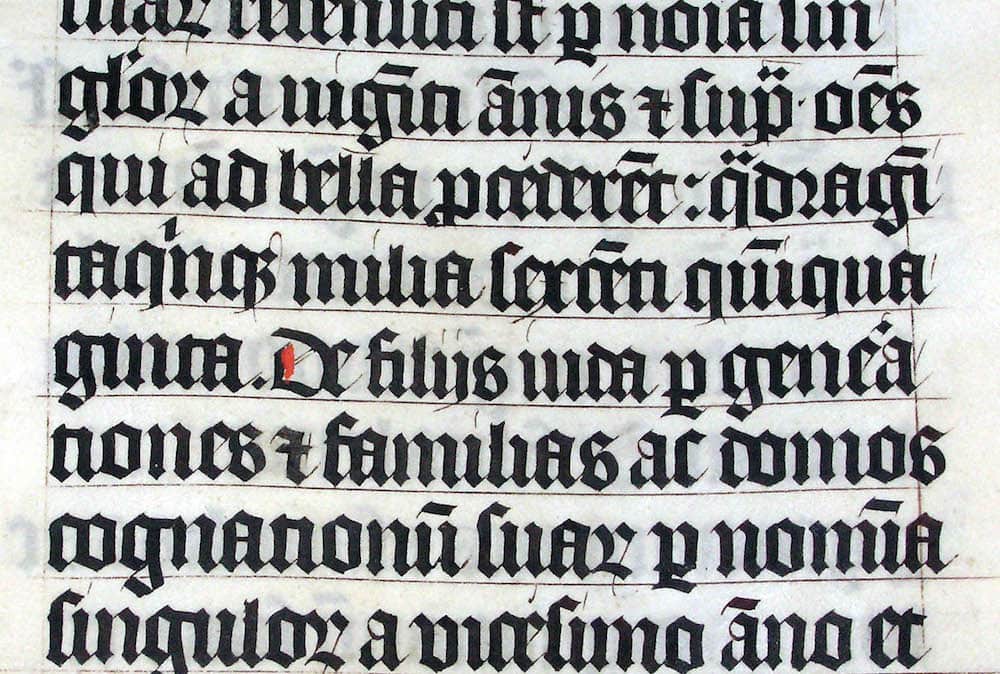
لديها عدد من الأسماء المختلفة - القوطية المصغرة ، و Blackletter ، والإنجليزية القديمة - ومجموعة متنوعة من الأشكال. يعتمد هذا على التفسيرات المختلفة في جميع أنحاء أوروبا ، والتي اعتبرت جميعها أن الخطوط القوطية "بربرية". على سبيل المثال ، Textura و Schwabacher و Fraktur و Cursiva و Hybrida.
المصطلح الآخر للخطوط القوطية يتعلق بالأسكندنافية “grotesk”. المحارف التي تستند إلى أشكال شمال أوروبا تشبه إلى حد كبير خطوط sans serif الكلاسيكية ، وفي كثير من الحالات يمكن أن تكون قابلة للتبديل.
كيفية اختيار الخطوط القوطية
يعتمد اختيارك للخط القوطي على النوع الذي تريد استخدامه. ومع ذلك ، من المحتمل أن ترغب في استخدام أحدهما كعنوان أو بأحجام أكبر. على سبيل المثال ، يمكن أن يتبع متغير grotesk نفس القواعد التي تتبعها sans serifs الأخرى في معظم الأحيان ، ولكنها قد تبدو مشتتة للغاية لنسختك الجسدية.
من المحتمل ألا يكون أسلوب الكتابة والنصوص في أوروبا الوسطى مناسبًا للنص الأساسي على الإطلاق ، على الرغم من أن هذه حالة استخدام نموذجية في أوجها. يمكن أن تكون هذه الأشكال غير قابلة للقراءة تمامًا في كثير من الحالات ، خاصة في الأحجام الأصغر - ومن ثم تكون الخطوط القوطية "بربرية".
نصيحتنا هي النظر في الطلب بإسهاب. ستكون الخطوط القوطية أفضل كعنوان أو كشعار لمستخدم مستهدف محدد.
18 خطًا قوطيًا رائعًا للعروض والعناوين وتصميم الشعار
خلال ما تبقى من هذا المنشور ، سنقوم بتشغيل بعض من أفضل الخطوط القوطية التي يمكن أن نجدها. طوال الوقت ، سنقدم لك أيضًا فكرة عن سعر كل منها ، إلى جانب مكان العثور عليها.
1. كامبريدج
تبدو كامبريدج وكأنها متغير "إنجليزي قديم" ، وستكون أفضل بأحجام كبيرة جدًا ، مثل الملصق أو التصميم المتناثر.
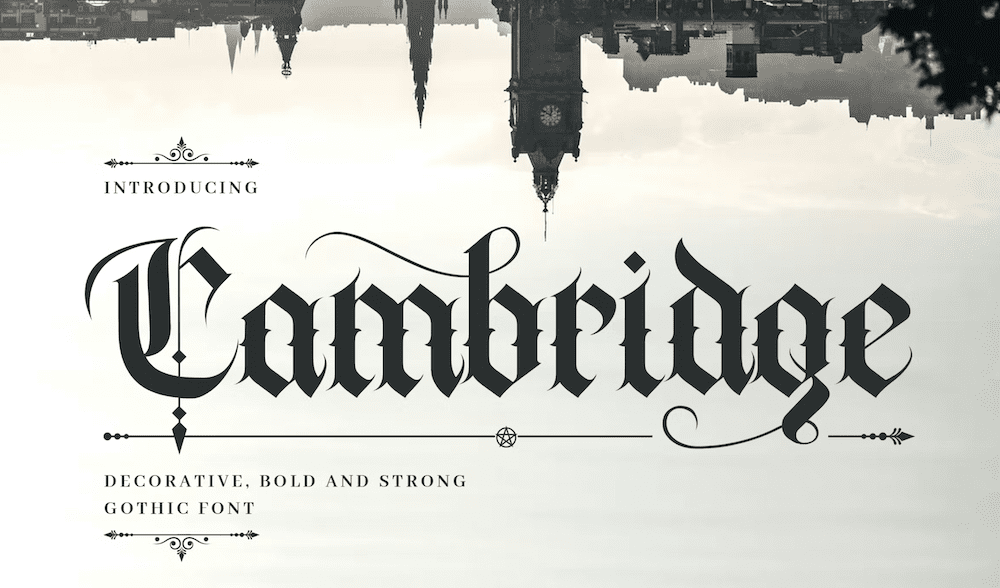
يأتي بثلاثة تنسيقات مختلفة - OTF و WOFF و TTF - ويتضمن مجموعة قياسية من الأحرف اللاتينية والأرقام وعلامات الترقيم والأحرف البديلة. كامبريدج مزخرفة ، ويمكن قراءتها بأحجام أصغر أيضًا - مما يثير الدهشة لمثل هذا الخط الخطي الرقيق.
2. أسماء
يذكرنا الخط التالي بخط Rennie Mackintosh التجاري من American Horror Story. ومع ذلك ، يأتي Asmath مع مجموعة أكثر مرونة وقابلة للاستخدام من الشخصيات serif.
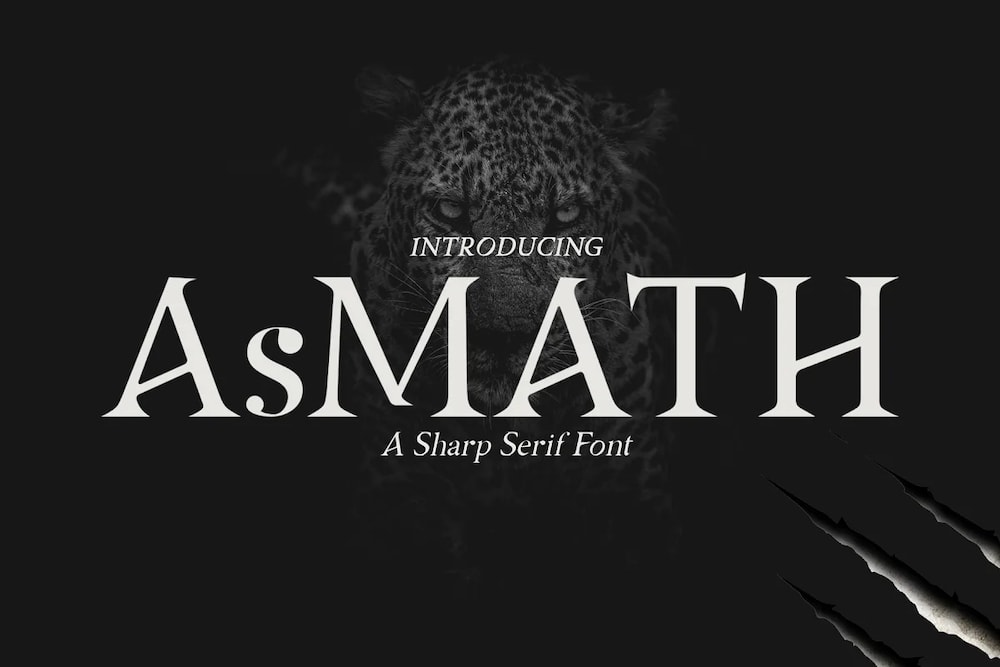
يمكنك استخدام هذا الخط في أنواع الأحرف الكبيرة والصغيرة ، ويأتي مع متغيرات عادية ومائلة وغامقة ومخططة. تبدو الأرقام رائعة هنا أيضًا ، حيث تتميز بتصميم "Oldstyle". بعبارات بسيطة ، هذا هو المكان الذي ستتجاوز فيه الأرقام الخط ، وربما تقدم زيادات أخرى أيضًا.
مقابل 12 دولارًا ، Asmath هو خط رائع للعرض والإعلان والتعبئة واللافتات والمزيد. لن يتناسب مع العديد من التطبيقات الحديثة ، إلا إذا كنت ترغب في إضفاء أجواء من الرعب. ومع ذلك ، فإنه يقوم بالأعمال التجارية مع المشروع الصحيح.
3. شيدر القوطية
الشيدر القوطي هو مثال على أسلوب غروتسك في شمال أوروبا. يحتوي على ثمانية أنماط مختلفة ، تتضمن اختلافات في الألواح والاستنسل ، وخيارات مائلة لكل منها.
يكتسب الخط طابعه من خلال تقنيات الرسم اليدوي ، وهو أسلوب "كل الأحرف الكبيرة". هذا يعني أنه يمكنك التبديل بين أصناف الأحرف الكبيرة والصغيرة والوصول إلى مئات الكلمات الرئيسية والحروف الرسومية والرموز والأحرف البديلة.
4. اسكتلندا
حان الوقت لتوجيه Braveheart بداخلك ، حيث أن اسكتلندا هي خطنا القوطي التالي. لن يحتوي هذا على قدر كبير من التنوع مثل الخطوط الأخرى في هذه القائمة ، ولكنه يقدم مثل نوع المدرسة القديمة ، القوطية ، من نوع Blackletter.
سوف تخدمك اسكتلندا بشكل أفضل كخط عرض. اعتمادًا على السياق ، يمكنك استخدام هذا على النشرات وبطاقات المعايدة وحتى للعروض التقديمية (مثل تقارير المدرسة.) نظرًا لأن اسكتلندا مجانية ، فلا توجد مخاطر لتنزيلها وتجربتها أيضًا!
5. ميدوسا القوطية
تأخذ Medusa Gothic الحروف الرومانية وتخلق "زخارف تشبه الأوراق" لخلق الحالة المزاجية المناسبة لأغلفة الكتب وليالي الألعاب وملصقات الأحداث التنكرية والمزيد. وهو عبارة عن متغير متعدد الأحرف ، ويمكن أن يؤدي التبديل بين الحالات إلى إضافة هذه الزيادات أو طرحها.
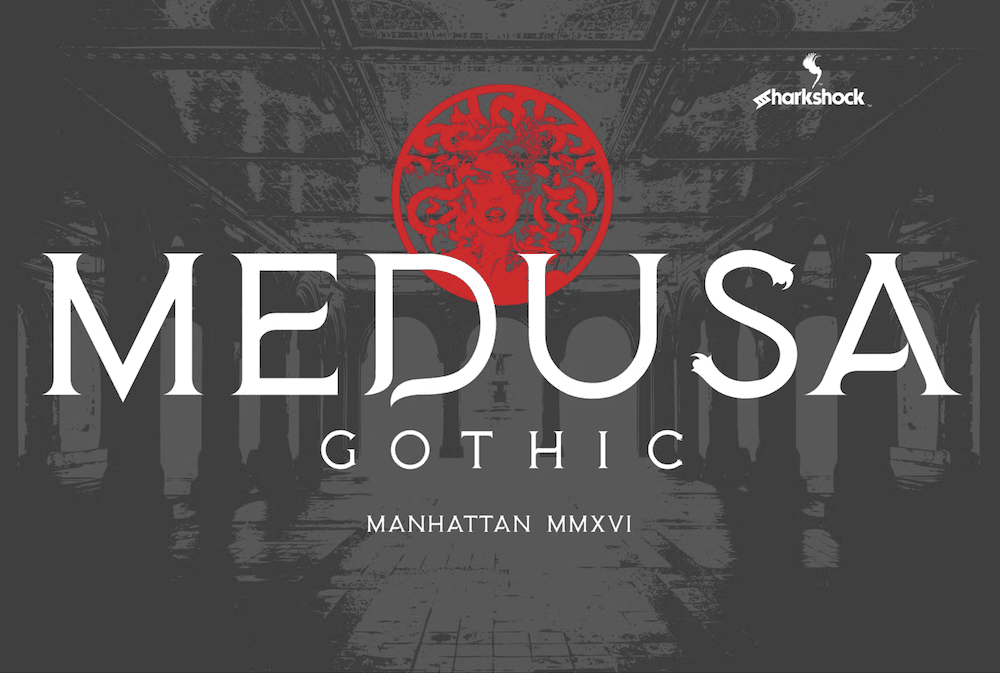
لديك مجموعة محدودة من علامات الترقيم ، لأن الخط ليس لنسخ النص الأساسي. Medusa Gothic هو خط عرض يتسم بالمرونة في الفضاء.
6. Quiska
في حين أن معظم الخطوط القوطية تبدو وكأنها تأتي مباشرة من فيلم رعب مصاص دماء ، فإن Quiska لديها أسلوب "فيكتوري" يتمتع بمستوى مذهل من المرونة.
يحتوي هذا الخط الرقيق على عدد كبير من الزخارف والأحرف المتساقطة والمزيد لإضفاء الحيوية على أحرف معينة (خاصة الأحرف الكبيرة). هناك أيضًا عدد من البدائل والأحرف المركبة أيضًا.
يمكننا أن نرى Quiska كنوع شعار لمقهى ، وعنوان على ملصق ، وخط عرض دعوة زفاف ، والمزيد. كما أنه يناسب التغليف وبطاقات المعايدة والكثير من التطبيقات الأخرى. مقابل 25 دولارًا ، تتمتع Quiska بالكثير من التنوع.
7. الفنير
يوفر Fenir ، وهو محرف بأحرف كبيرة ، الكثير من المشاعر القديمة التي يمكن أن تعمل مع منشورات الموسيقى والعلامات التجارية لملابس الدنيم والتطبيقات المماثلة.
هذا الخط القوطي من نوع sans serif ، وهو مشابه تمامًا كما هو الحال. لديك القدرة على التبديل بين الأحرف الكبيرة والصغيرة لبعض الأحرف البديلة ، والقليل من الأشياء الأخرى. يمكن أن يكون مثاليًا إذا كان Fenir يجلب المظهر المناسب لتصميمك.
8. بروت
يجب ألا تكون الميزانية عائقًا أمام العنوان الرائع أو خط التسمية التوضيحية. يمكن لـ Brut حل هذه المشكلات ، حيث إنها لا تكلف شيئًا ولديها إحساس السبعينيات بحروفها. هذا الخط sans-serif gothic هو محرف ذو أحرف كبيرة ، وفي أعيننا تذكر Microgramma Bold Extended ، والتي تشتهر باستخدامها في Star Trek.
على الرغم من غلاف واحد فقط ، فإن Brut متعدد الاستخدامات. في الأحجام الضخمة ، إنه خط عنوان رائع. ومع ذلك ، في الأحجام الأصغر ، يمكنك استخدام المسافات لفتح كل حرف. علاوة على ذلك ، يمكنك رؤية الشكل والتكوين الفريد لكل حرف بشكل أفضل. قد يكون Brut مجانيًا ، لكنه رائع وقابل للاستخدام.
9. كيلوميناتي
ستعجب فرق الروك الضبابية بمظهر كيلوميناتي. إنه يحد قليلاً على حافة غير قابلة للقراءة في الأماكن ، ولكنه يتمتع بتنوع رائع داخل العبوة.
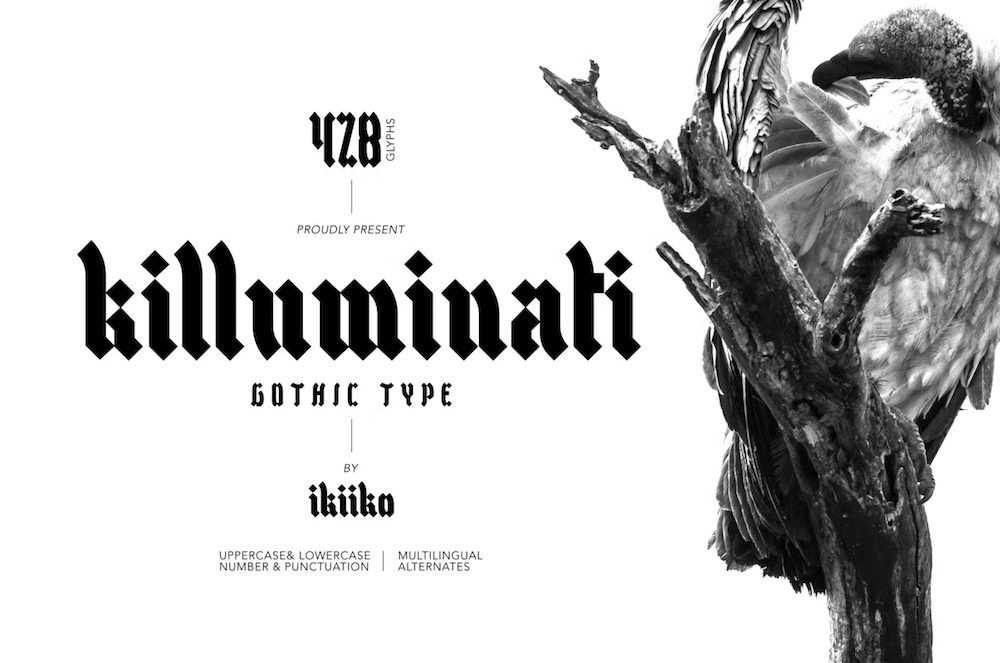
الخط هو نمط حديث من Blackletter ، ويأتي مع متغيرات صغيرة أيضًا. باستخدام المسافة بين الحروف الصحيحة ، يمكنك استخدام هذا في نسخة العنوان الفرعي. هناك أيضًا الكثير من الشخصيات البديلة ، والحروف الرسومية ، والشخصيات متعددة اللغات.
10. Hurscol
لا يبدو Hurscol كخط قوطي ، لكن هذا الخط المرسوم يدويًا والمستوحى من Americana يحتوي على جميع السمات المميزة.
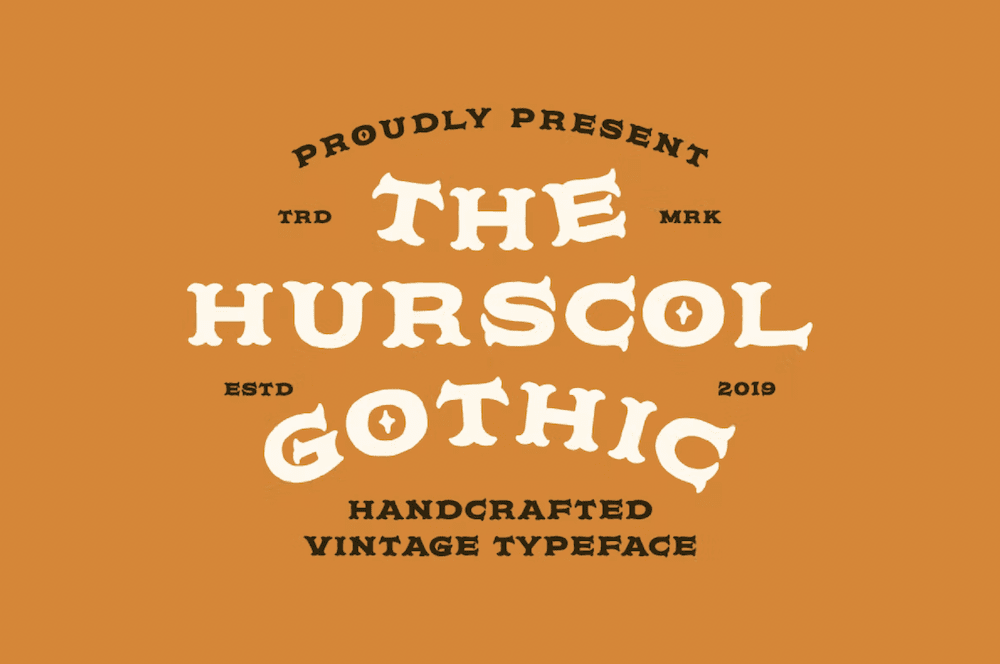
إنه يعطي مظهرًا رائعًا في منتصف القرن العشرين ، وسيبدو رائعًا كشعار لمتاجر الملابس القديمة المستعملة. في الواقع ، كلما كان هذا الخط أكبر ، كان ذلك أفضل ، لأنه يناسب الملصقات واللافتات والتصميمات الرجعية العامة. إذا أعطيته مساحة كافية ، يمكنك حتى تصغيره لاستخدامه على الشارات والملصقات.
11. غريب من خلال
Stranger Through هو خط قوطي يناسب تصميمات من نوع الرعب ، بالنظر إلى الشكل الزاوي للشخصيات.
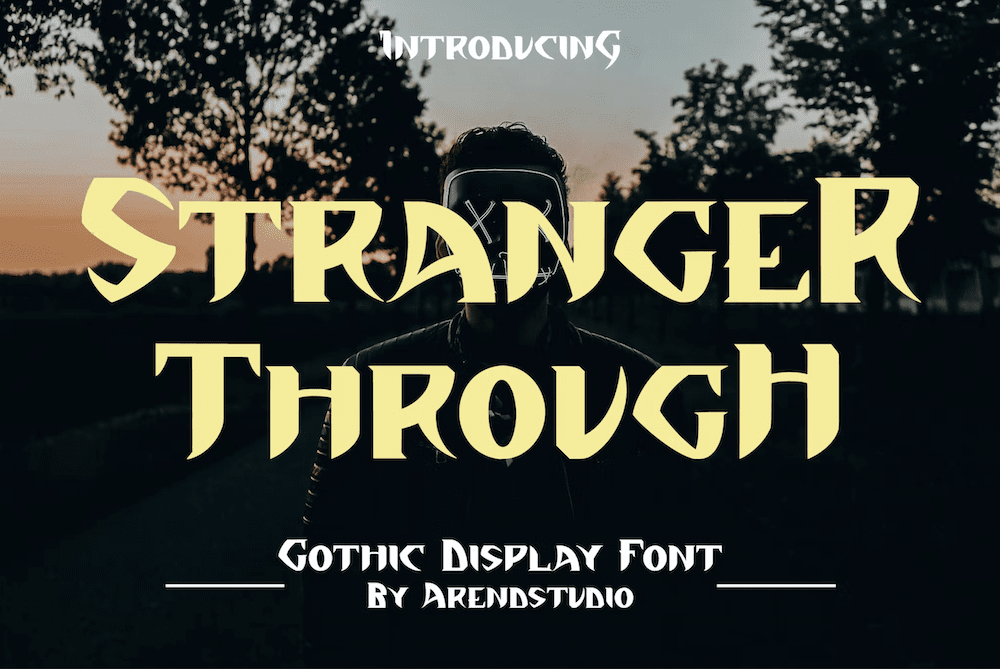
لن تستخدم هذا لنسخ الجسم ، لكن هذا sans serif يعمل بشكل جيد. تأتي الحزمة مع اختلافات كبيرة وأرقام ورموز وعلامات ترقيم وحتى توفر "dingbats". هذه فواصل أقسام أو عناصر إطار صندوق - مفيدة إذا كنت بحاجة إلى تقديم نسختك.
12. حريق منتصف الشتاء
إذا أخذت خط ITC Benguiat من Stranger Things ، وقمت بتشغيل بعض ألبومات Black Sabbath ، فستحصل على Midwinter Fire. إنه قوطي وعتيق وسيبدو رائعًا على أغلفة الكتب أو الرسوم الهزلية.
في الواقع ، إنه يشعر به في الثمانينيات - مناسب بالنظر إلى الإلهام الواضح. قد لا تتمتع Midwinter Fire بالكثير من التنوع ، ولكنها تناسب المشاريع المناسبة مباشرة. علاوة على ذلك ، لديك عدد من بدائل التسطير أيضًا ، والتي ستساعد في بناء بعض التصميم والبنية في كل ما تقوم بإنشائه.
13. غوريلا بير
من السهل اكتشاف كيف يعتقد منشئو Gorilla Beer أن المستخدم سيطبق هذا الخط. إنه نوع عتيق من نوع sans serif مع مجموعة من الخيارات المدروسة.
سوف يناسب Gorilla Beer الشعارات والتطبيقات النصية الجريئة. تُظهر أمثلة مسبك النوع أيضًا قمصانًا. ستعمل أي مشاريع من النوع القديم - الحلاقون الذكور ، المقاهي ، تجار الجعة - مع هذا الخط. قد يكون مزخرفًا جدًا لشعارات الفرقة ، رغم ذلك.
14. راكولا
تتوابل لعبة Racula وتقلل من عنصر الخط القوطي ، حيث إنها تضفي جوًا من المرح والحيوية ، على الرغم من الإلهام الأساسي.
إنه Serif ، ويأتي مع مزيج من الأحرف الكبيرة والصغيرة ، والأحرف المركبة ، والبدائل. إذا كنت ترغب في إضفاء طابع `` مخيف '' بدلاً من الطابع القوطي الحقيقي ، ربما لحفلات أعياد الميلاد والدعوات ومشاريع عيد الهالوين للأطفال ، فإن Racula ستناسب الفاتورة.
15. فانكوفر
من بين الخطوط القوطية الغروتسك الأخرى ، تشترك فانكوفر مع أمثال Impact و Helvetica و Arial. هذا لديه "حركة" أكثر ، وله إحساس مرسوم باليد.
سيكون الخط مثاليًا لمشاريع السماح ، مثل الملصقات والعناوين والمزيد. باختصار ، كلما زاد الحجم الذي تحتاجه للخط ، كلما كان حجم فانكوفر مناسبًا.
16. السيد بلو سكاي
على النقيض تمامًا ، يعد Mr Blue Sky أيضًا خطًا قوطيًا ، ولكن هذا الخط sans-serif هو طريقة ملتوية ومرحة لإضافة حروف كبيرة الحجم إلى مشاريعك.
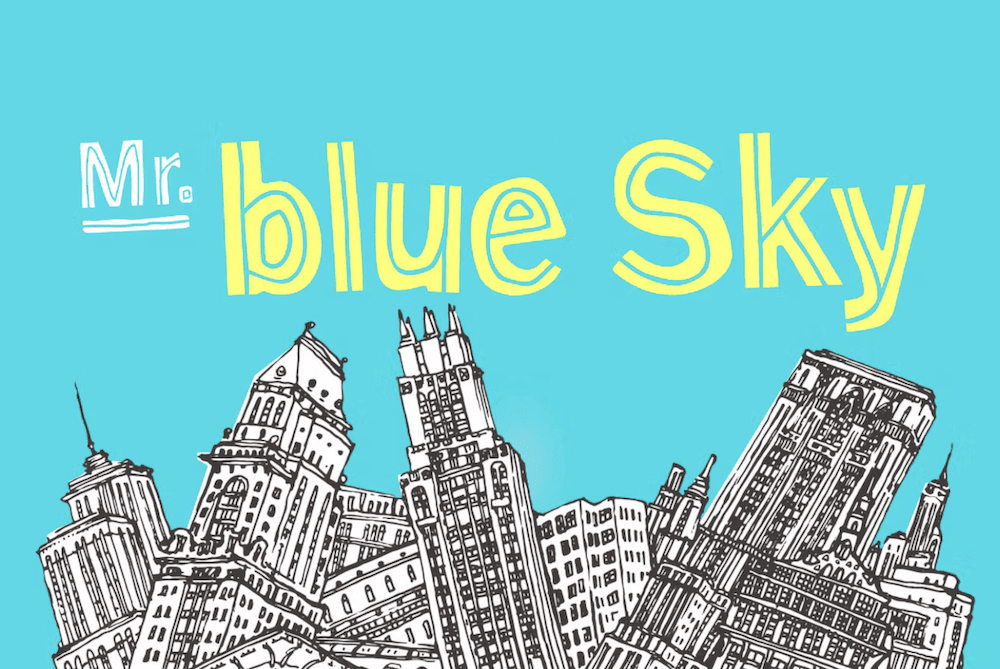
يحتوي الخط القوطي على ردود فعل صيفية ، وهو تناقض آخر مع الألوان الداكنة لمحارف اللغة الإنجليزية القديمة والبلاكليت. ستكون الشعارات والملصقات على وجه الخصوص حالة استخدام مثالية للسيد بلو سكاي.
17. كافر
يمثل Godbless ما يسمى بـ "خطوط الوشم" - وهو مؤشر رئيسي لكيفية استخدام هذا الخط. إنه أحد الأساليب الأكثر حداثة في هذه القائمة. ستستخدم Godbless على الشعارات والملصقات أيضًا - فهي تعطي "مشاعر البحار" ولكنها تستحضر أيضًا أفلامًا مثل Indiana Jones و Jumanji.
الخط هو الخط الذي سيبرز أكثر إذا كنت تستخدم عددًا أقل من الأحرف. يبدو متينًا ، ونحب الزخارف والأرقام.
18. الألفية
كخط grotesk ، فإن Millenium لهيكل وحالات استخدام مماثلة لفانكوفر. إنه خط ستستخدمه كخط عملاق كبير وجريء على الملصقات.
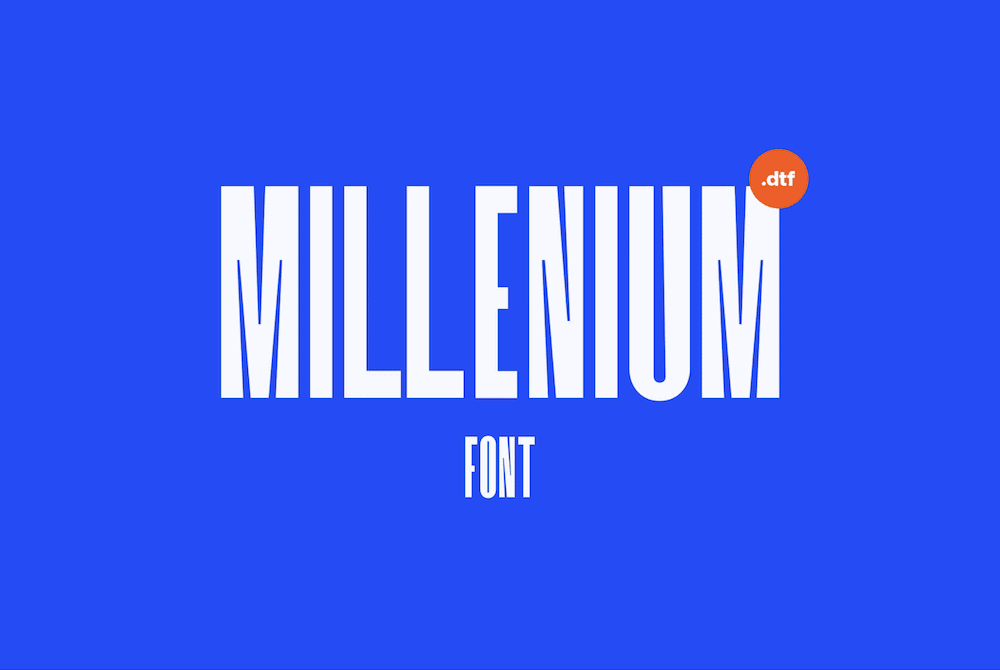
نعتقد أن هناك ارتباطًا بهذا الخط في الستينيات ، ويمكنك رؤيته كخط عنوان لفن الغلاف الموسيقي. جزء من هذا بسبب سهولة القراءة ، على الرغم من كونه محرفًا مكثفًا. يلعب عدم تناسق Millenium أيضًا دورًا في هذا ، ويضيف طبقة خفية من الغرابة التي تزيل حافة الخطوط الخشنة القاسية.
تغليف
إذا كان لديك تصميم يجب أن يدلي ببيان ، فقد تكون الخطوط القوطية هي الطريقة التي تفعل بها ذلك. إنها تعطي أجواء رائعة للأعمال التجارية الحديثة مثل صالون الوشم أو البار. ومع ذلك ، فأنت بحاجة إلى اختيار الخيار الصحيح لمنع تحول إبداعك إلى فوضى غير مقروءة.
يمنحك هذا المنشور الكثير للاختيار من بينها بعدد من الأنماط والأنواع المختلفة. ومع ذلك ، فإن اختيارنا يذهب إلى كامبريدج لأسلوبها الإنجليزي القديم شبه المثالي. نحن نحب كيلوميناتي أيضًا لأسباب مماثلة. مع الخط القوطي الجيد ، فإن الأجواء التي تثيرها كلها مهمة لكيفية نجاحها.